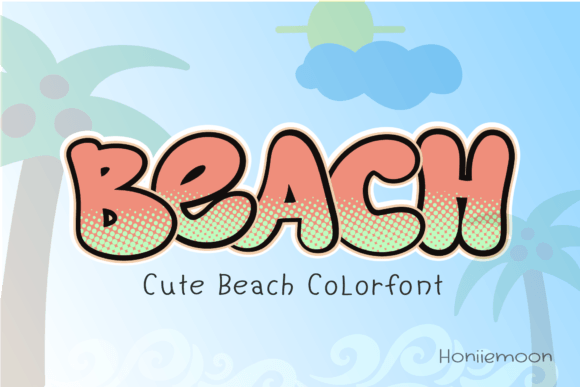
Beach Font
Beach Font – الخط المثالي لتصاميمك الصيفية!
اصنع أجواءً صيفية منعشة مع Beach Font، الخط الذي يجسد إحساس الرمال الدافئة، الأمواج الهادئة، واللحظات المشرقة على الشاطئ. يتميز هذا الخط بأسلوبه العصري والأنيق، مما يجعله مثاليًا لتصميم الشعارات، العناوين الجذابة، منشورات السوشيال ميديا، بطاقات الدعوة، والعديد من المشاريع الإبداعية.
???? المميزات:
✔ تصميم أنيق وعصري
✔ يدعم الحروف الكبيرة والصغيرة
✔ مثالي للعناوين والتصاميم المبهجة
أضف لمسة من الحيوية إلى تصاميمك مع Beach Font واجعل كل مشروع ينبض بروح الصيف! ????☀